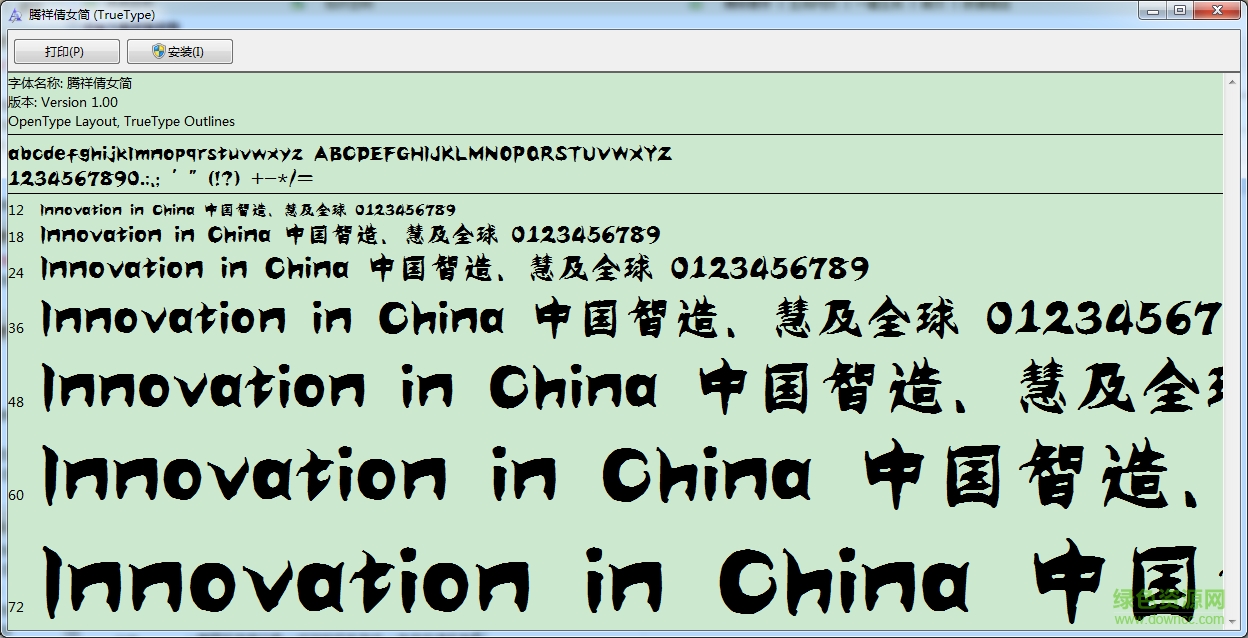
騰祥倩女簡是一款獨具特色的藝術字體,這款字體字形清新秀逸,姿態(tài)婀娜似少女亭亭玉的倩女,字形十分有范,喜歡的朋友歡迎來綠色資源網下載使用!
騰祥倩女簡體,美術字體,此款字突出的靚點是將書法體與美術體巧妙結合渾然天成。利用行書的筆法,筆畫瀟灑流落,翰逸神飛,重筆觸大膽用墨,輕筆觸干凈利落,偏旁與字身勾連貫通自如流暢,又融入美術字的書寫特征很好地控制張力,保證每個字的風格統(tǒng)一、粗細得當、易于閱讀。然筆墨自然流動間又結構端莊。